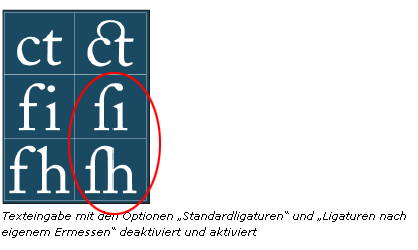
Gut, daß die Ligaturen nicht so funktionieren wie im Adobe HelpCenter visualisiert ... ;)
Erschreckend, dass das noch immer so ist! Steht nämlich schon als abrschreckendes Beispiel in Detailtypografie.
Naja ich hab auch zweimal draufschauen müssen, um zu erkennen, was eigentlich genau falsch ist.
Ach Schitt, ich dachte ja naiv noch immer, es habe sich nur der Grafiker verhauen als er von Hand irgendwelche Glyphen aus den Sonderzeichen gefischt hat. Das ist wirklich im Font falsch :shock: :?:
nein, falsch verstanden (zu knapp formuliert):
Wenn Photoshop es so darstellen würde wie im Helpcenter in der Grafik, müsste Photoshop ja bewusst die Schriftvorgaben ignorieren, und f durch langes s ersetzen, damit das zustande kommt.
Ich denke da hat der Grafiker sich die Ligaturen von Hand zusammengeklickt aus der Glyphentabelle, und hat nicht aufgepasst.